ฟอนต์เปลี่ยน ยอดขายเปลี่ยน! เจาะ 5 เทรนด์ ‘ตัวอักษรไทย’ ปี 2026 สร้างแบรนด์ให้ดูแพง
ในโลกธุรกิจที่มีการแข่งขันสูง แนวคิดที่ว่า ฟอนต์เปลี่ยน ยอดขายเปลี่ยน! เจาะ 5 เทรนด์ ‘ตัวอักษรไทย’ ปี 2026 สร้างแบรนด์ให้ดูแพง ได้กลายเป็นกลยุทธ์สำคัญสำหรับผู้ประกอบการและนักการตลาด การเลือกใช้ตัวอักษรไม่ใช่เพียงองค์ประกอบด้านความสวยงามอีกต่อไป แต่เป็นเครื่องมือทางจิตวิทยาที่ทรงพลังในการสื่อสารบุคลิกภาพของแบรนด์ สร้างการจดจำ และส่งผลโดยตรงต่อการตัดสินใจซื้อของผู้บริโภค การทำความเข้าใจเทรนด์การออกแบบตัวอักษรที่กำลังจะมาถึง จึงเป็นกุญแจสำคัญในการสร้างความได้เปรียบและยกระดับภาพลักษณ์ของธุรกิจให้ดูหรูหราและน่าเชื่อถือ
ประเด็นสำคัญที่นักการตลาดและเจ้าของธุรกิจไม่ควรพลาด
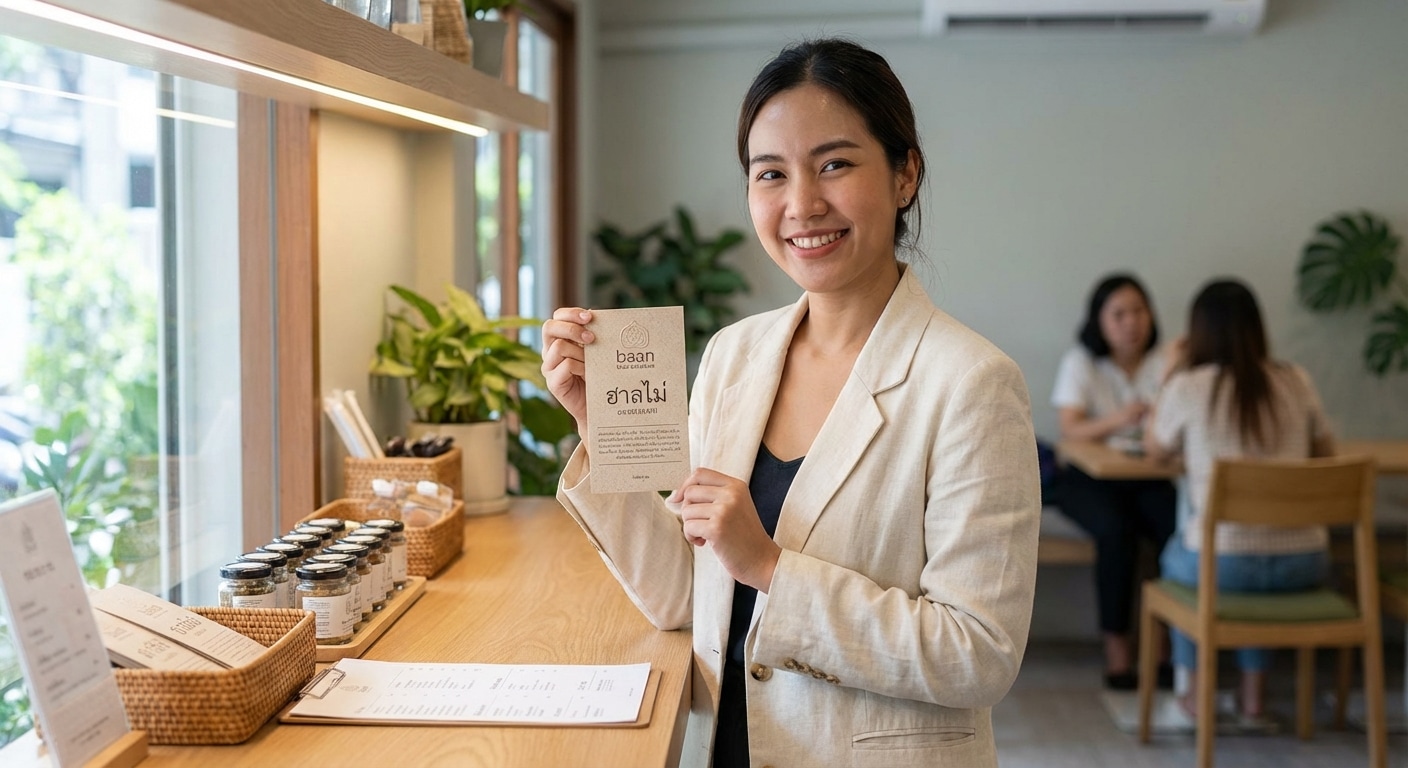
- ความหรูหราแบบทันสมัย (Modern Luxury): เทรนด์ฟอนต์ปี 2026 มุ่งเน้นการสร้างความรู้สึกพรีเมียมผ่านการใช้ตัวอักษรขนาดใหญ่ (Oversized) ฟอนต์เชิงทดลอง (Experimental) และการผสมผสานวัฒนธรรม (Cross-Cultural) เพื่อสร้างเอกลักษณ์ที่โดดเด่น
- จิตวิทยาผ่านตัวอักษร: ฟอนต์ที่มีความโค้งมนให้ความรู้สึกอบอุ่นและเป็นมิตร ในขณะที่ฟอนต์แบบ Serif สื่อถึงความน่าเชื่อถือและความคลาสสิก การเลือกใช้ที่เหมาะสมช่วยสร้างความไว้วางใจให้กับแบรนด์
- เอกลักษณ์ความเป็นไทยในบริบทสากล: การนำแรงบันดาลใจจากรากเหง้าของตัวอักษรไทยโบราณมาผสมผสานกับการออกแบบสมัยใหม่ เป็นอีกหนึ่งแนวทางที่ช่วยสร้างความแตกต่างและน่าจดจำในตลาดโลก
- ความยืดหยุ่นในยุคดิจิทัล: อัตลักษณ์องค์กร (Corporate Identity) ที่ยืดหยุ่นสามารถปรับเปลี่ยนโลโก้หรือตัวอักษรตามบริบทของสื่อดิจิทัลได้ จะช่วยสร้างความทันสมัยและเพิ่มการมีส่วนร่วมของผู้บริโภค
- ฟอนต์มีผลต่อยอดขาย: การปรับเปลี่ยนฟอนต์บนบรรจุภัณฑ์ เมนูอาหาร หรือสื่อประชาสัมพันธ์ สามารถยกระดับการรับรู้มูลค่าของสินค้าและบริการ นำไปสู่การเพิ่มขึ้นของยอดขายได้อย่างมีนัยสำคัญ
ทำไมการเลือกฟอนต์จึงเป็นมากกว่าแค่ความสวยงามในปี 2026
ในยุคที่ผู้บริโภคถูกรายล้อมด้วยข้อมูลและสื่อต่างๆ มากมาย การสร้างความประทับใจแรก (First Impression) กลายเป็นสิ่งสำคัญอย่างยิ่ง ตัวอักษร หรือ Typography คือหนึ่งในองค์ประกอบแรกๆ ที่ผู้บริโภคสัมผัสและมีปฏิสัมพันธ์ด้วย ไม่ว่าจะเป็นบนโลโก้, บรรจุภัณฑ์สินค้า, เว็บไซต์ หรือโพสต์บนโซเชียลมีเดีย ฟอนต์สามารถกำหนดการรับรู้ของลูกค้าที่มีต่อแบรนด์ได้ทันที ก่อนที่พวกเขาจะได้อ่านเนื้อหาทั้งหมดด้วยซ้ำ
สำหรับผู้ประกอบการขนาดกลางและขนาดย่อม (SME), นักออกแบบ, และนักการตลาดในประเทศไทย การเข้าใจเทรนด์ฟอนต์ปี 2026 จึงเป็นสิ่งจำเป็น ข้อมูลพฤติกรรมผู้บริโภคชี้ให้เห็นว่าคนไทยใช้เวลากับโซเชียลมีเดียโดยเฉลี่ยถึง 20 ชั่วโมง 45 นาทีต่อสัปดาห์ ซึ่งหมายความว่าแบรนด์มีโอกาสสร้างการรับรู้ผ่านภาพลักษณ์บนแพลตฟอร์มดิจิทัลได้อย่างมหาศาล การเลือกฟอนต์ที่ทันสมัย สื่อสารตัวตนของแบรนด์ได้ชัดเจน และสอดคล้องกับเทรนด์ระดับโลกที่ปรับใช้กับบริบทไทย จะช่วยให้แบรนด์ของคุณโดดเด่นจากคู่แข่ง สร้างความน่าเชื่อถือ และกระตุ้นให้เกิดการจดจำ ซึ่งท้ายที่สุดแล้วจะนำไปสู่ความภักดีต่อแบรนด์และยอดขายที่เพิ่มขึ้น
เจาะลึก 5 เทรนด์ฟอนต์ไทยที่จะกำหนดทิศทางของแบรนด์ในปี 2026
แนวโน้มการออกแบบตัวอักษรในปี 2026 สะท้อนถึงความต้องการของผู้บริโภคที่มองหาทั้งความหรูหรา ความจริงใจ และประสบการณ์ที่ไม่เหมือนใคร เทรนด์เหล่านี้สามารถนำมาปรับใช้กับตัวอักษรไทยเพื่อสร้างสรรค์งานออกแบบที่ทรงพลังและตอบโจทย์ตลาดได้อย่างลงตัว
เทรนด์ที่ 1: Bold & Experimental Typography – พลังของตัวอักษรเชิงทดลองขนาดใหญ่
เทรนด์นี้คือการฉีกกรอบการออกแบบตัวอักษรแบบเดิมๆ โดยเน้นการใช้ฟอนต์ขนาดใหญ่พิเศษ (Oversized) และการจัดวางองค์ประกอบที่ท้าทายสายตา เพื่อสร้างจุดสนใจและสื่อสารข้อความหลัก (Key Message) อย่างทรงพลัง
ลักษณะเด่น: การใช้ฟอนต์ที่มีน้ำหนักมาก (Bold, Extra Bold, Black) หรือฟอนต์ประเภท Serif ที่มีรายละเอียดของเส้นสายที่ซับซ้อนและสวยงาม มาขยายให้มีขนาดใหญ่จนกลายเป็นองค์ประกอบหลักของงานออกแบบ การจัดวางอาจจะไม่เป็นระเบียบตามปกติ เพื่อสร้างความรู้สึกที่แปลกใหม่และน่าตื่นเต้น แนวคิดนี้มุ่งสร้างความรู้สึกแบบ Modern Luxury ที่ทำให้แบรนด์ดูมีระดับและน่าจดจำ
การประยุกต์ใช้กับแบรนด์ไทย: เหมาะอย่างยิ่งสำหรับแบรนด์แฟชั่น, นิตยสาร, สินค้าไลฟ์สไตล์, หรือธุรกิจที่ต้องการสร้างภาพลักษณ์ที่กล้าหาญและเป็นผู้นำ สามารถนำไปใช้บนหน้าปกสินค้า, โปสเตอร์โฆษณา, ป้ายหน้าร้าน หรือเป็นภาพ Hero Image บนหน้าเว็บไซต์ เพื่อดึงดูดความสนใจได้ในทันที
เทรนด์ที่ 2: Smooth It Over – ความละมุนนุ่มนวลที่สร้างความไว้วางใจ
สวนทางกับความแข็งกร้าวของเทรนด์แรก เทรนด์นี้มุ่งเน้นไปที่การใช้ฟอนต์ที่มีความโค้งมน ลดเหลี่ยมมุมที่แหลมคม เพื่อสร้างความรู้สึกที่อบอุ่น, เป็นมิตร, เข้าถึงง่าย และน่าไว้วางใจ แต่ยังคงไว้ซึ่งความหรูหราและพรีเมียม
ลักษณะเด่น: ตัวอักษรจะมีลักษณะกลมมน ปลายเส้นมักจะโค้งมนแทนที่จะเป็นเส้นตัดตรง ให้ความรู้สึกนุ่มนวลสบายตา จิตวิทยาของรูปทรงโค้งมนสื่อถึงความปลอดภัย ความสบายใจ และความเป็นกันเอง
การประยุกต์ใช้กับแบรนด์ไทย: เหมาะสมอย่างยิ่งกับแบรนด์ที่เกี่ยวข้องกับสุขภาพและความงาม, ผลิตภัณฑ์สำหรับแม่และเด็ก, ธุรกิจอาหารและเครื่องดื่ม, ธุรกิจบริการ เช่น สปา, คลินิก หรือคาเฟ่ที่ต้องการสร้างบรรยากาศที่เป็นมิตรและเชื้อเชิญ การใช้ฟอนต์ลักษณะนี้บนโลโก้หรือบรรจุภัณฑ์จะช่วยสร้างความสัมพันธ์ที่ดีกับลูกค้าและทำให้แบรนด์ดูน่าเชื่อถือ
เทรนด์ที่ 3: Cross-Cultural Type – เสน่ห์ข้ามวัฒนธรรมในตัวอักษรไทย
เทรนด์นี้คือการเฉลิมฉลองความเป็นเอกลักษณ์ทางวัฒนธรรม โดยการนำองค์ประกอบจากรากเหง้าของตัวอักษรในแต่ละท้องถิ่นมาผสมผสานกับการออกแบบที่ทันสมัย เพื่อสร้างอัตลักษณ์ที่ไม่เหมือนใคร
ลักษณะเด่น: การดึงแรงบันดาลใจจากรูปแบบตัวอักษรไทยย้อนยุค, ตัวอักษรที่มีเชิงฐานแบบไทย, หรือแม้กระทั่งการนำลวดลายจากงานหัตถกรรมพื้นบ้านมาประยุกต์เป็นส่วนหนึ่งของตัวอักษร ผลลัพธ์ที่ได้คือฟอนต์ที่มีเรื่องราว มีความสดใหม่ และสื่อถึงความเป็นต้นตำรับอย่างชัดเจน
การประยุกต์ใช้กับแบรนด์ไทย: เป็นโอกาสที่ดีสำหรับแบรนด์ที่ต้องการชูจุดเด่นความเป็นไทย เช่น สินค้า OTOP ที่ต้องการยกระดับสู่ตลาดพรีเมียม, โรงแรมและรีสอร์ท, ร้านอาหารไทย, หรือแบรนด์ผลิตภัณฑ์สมุนไพร การใช้ฟอนต์ลักษณะนี้ช่วยสร้างความแตกต่างที่น่าสนใจและดึงดูดทั้งลูกค้าชาวไทยและชาวต่างชาติ
เทรนด์ที่ 4: Pharma Serif – ความหรูหราจากแรงบันดาลใจยุคเก่า
ได้รับแรงบันดาลใจจากฟอนต์ประเภท Serif ที่มีโครงสร้างชัดเจนและอ่านง่าย ซึ่งเคยนิยมใช้บนบรรจุภัณฑ์ยาในอดีต แต่ถูกนำมาตีความใหม่ให้มีความทันสมัยและหรูหรามากขึ้น
ลักษณะเด่น: เป็นฟอนต์ Serif ที่มีความสมดุลระหว่างประโยชน์ใช้สอย (Utilitarian) และความสวยงามทางศิลปะ มีรายละเอียดของเส้นที่คมชัดและสง่างาม ให้ความรู้สึกน่าเชื่อถือ, เป็นทางการ, และมีคุณภาพสูง
การประยุกต์ใช้กับแบรนด์ไทย: เหมาะสำหรับแบรนด์ที่ต้องการสร้างภาพลักษณ์ของความเชี่ยวชาญและความน่าเชื่อถือ เช่น แบรนด์เวชสำอาง (Dermo-cosmetics), ผลิตภัณฑ์ดูแลสุขภาพระดับพรีเมียม, ธุรกิจที่ปรึกษา, หรือสถาบันการเงิน การใช้ฟอนต์ Pharma Serif ในโลโก้หรือหัวข้อสำคัญจะช่วยสร้างสมดุลระหว่างความคลาสสิกและความทันสมัยได้อย่างลงตัว
เทรนด์ที่ 5: Lingua-Lettering & Halftone Blur – ลูกเล่นทางภาษาและภาพที่น่าจดจำ
เทรนด์สุดท้ายนี้เน้นไปที่การสร้างสรรค์ลูกเล่นทางภาพเพื่อดึงดูดความสนใจในโลกดิจิทัลที่เต็มไปด้วยการแข่งขัน โดยใช้เทคนิคที่สนุกสนานและน่าจดจำ
ลักษณะเด่น: มีสองแนวทางหลัก คือ Lingua-Lettering ซึ่งเป็นการผสมผสานตัวอักษรจากหลายภาษา (เช่น ไทยและอังกฤษ) เข้าไว้ด้วยกันอย่างมีศิลปะ และ Halftone Blur คือการใช้เทคนิคจุดไข่ปลา (Dots) ขนาดใหญ่มาสร้างเป็นตัวอักษรหรือพื้นหลัง ทำให้เกิดเอฟเฟกต์ที่ดูเบลอแต่ยังมีโครงสร้างที่ชัดเจน
การประยุกต์ใช้กับแบรนด์ไทย: เหมาะสมอย่างยิ่งสำหรับการสร้างแบรนด์บนแพลตฟอร์มดิจิทัล เช่น คอนเทนต์สำหรับโซเชียลมีเดีย, แบนเนอร์โฆษณาออนไลน์, หรือแคมเปญการตลาดที่ต้องการสร้างกระแส (Viral) เทคนิคนี้ช่วยให้แบรนด์ดูทันสมัย, เข้าถึงง่าย, และสร้างการมีส่วนร่วมกับกลุ่มเป้าหมายที่เป็นคนรุ่นใหม่ได้เป็นอย่างดี
สรุปภาพรวมเทรนด์ฟอนต์ไทย 2026
| เทรนด์ (Trend) | ลักษณะเด่น (Key Feature) | เหมาะกับธุรกิจประเภท | สร้างความรู้สึก (Evokes Feeling) |
|---|---|---|---|
| Bold & Experimental | ตัวอักษรขนาดใหญ่, จัดวางแปลกใหม่, Serif รายละเอียดสูง | แฟชั่น, ไลฟ์สไตล์, นิตยสาร, แบรนด์ที่ต้องการเป็นผู้นำ | หรูหรา, ทันสมัย, กล้าหาญ, โดดเด่น |
| Smooth It Over | ฟอนต์โค้งมน, ลดมุมแหลม, นุ่มนวล | สุขภาพ, ความงาม, สินค้าเด็ก, คาเฟ่, สปา | อบอุ่น, เป็นมิตร, น่าไว้วางใจ, เข้าถึงง่าย |
| Cross-Cultural Type | ผสมผสานรากเหง้าวัฒนธรรมไทยกับการออกแบบสมัยใหม่ | สินค้า OTOP, ร้านอาหารไทย, โรงแรม, แบรนด์ที่มีเรื่องราว | มีเอกลักษณ์, น่าค้นหา, จริงใจ, มีเรื่องราว |
| Pharma Serif | Serif ที่มีโครงสร้างชัดเจน, สมดุล, สง่างาม | เวชสำอาง, การเงิน, ที่ปรึกษา, แบรนด์ที่เน้นความเชี่ยวชาญ | น่าเชื่อถือ, เป็นมืออาชีพ, มีคุณภาพ, คลาสสิก |
| Lingua-Lettering | ผสมหลายภาษา, ใช้เทคนิคภาพ (Halftone) | แบรนด์ดิจิทัล, สินค้าสำหรับคนรุ่นใหม่, แคมเปญการตลาด | สนุกสนาน, ทันสมัย, สร้างสรรค์, น่าจดจำ |
กลยุทธ์การเลือกและจับคู่ฟอนต์ไทยสำหรับ SME
การรู้จักเทรนด์เป็นเพียงจุดเริ่มต้น สิ่งที่สำคัญกว่าคือการนำไปปรับใช้ให้เข้ากับแบรนด์ของตนเองได้อย่างมีประสิทธิภาพ การเลือกและจับคู่ฟอนต์ไม่ใช่เรื่องที่ซับซ้อนหากเข้าใจหลักการพื้นฐาน
หลักการพื้นฐานในการจับคู่ฟอนต์
- สร้างความแตกต่าง (Contrast): หลักการที่สำคัญที่สุดคือการจับคู่ฟอนต์ที่มีความแตกต่างกันอย่างชัดเจน เช่น การใช้ฟอนต์แบบ Serif (มีเชิง) สำหรับหัวข้อ และใช้ฟอนต์ Sans-serif (ไม่มีหัว) สำหรับเนื้อหา เพื่อสร้างลำดับชั้นในการอ่านและทำให้ข้อความอ่านง่ายขึ้น
- กำหนดลำดับชั้นของข้อมูล (Hierarchy): ใช้ขนาด, น้ำหนัก (ความหนา), และสไตล์ของฟอนต์เพื่อนำทางสายตาของผู้อ่าน หัวข้อหลักควรโดดเด่นที่สุด ตามมาด้วยหัวข้อย่อย และเนื้อหาตามลำดับ
- รักษาบุคลิกของแบรนด์ (Brand Personality): ฟอนต์ที่เลือกใช้ต้องสอดคล้องกับบุคลิกของแบรนด์ หากแบรนด์ของคุณดูสนุกสนานและเป็นกันเอง การเลือกใช้ฟอนต์ที่เป็นทางการและเคร่งขรึมอาจสร้างความสับสนให้กับลูกค้าได้
- จำกัดจำนวนฟอนต์: เพื่อความเป็นระเบียบและไม่ทำให้งานออกแบบดูรกจนเกินไป ควรจำกัดการใช้ฟอนต์ในงานออกแบบหนึ่งชิ้นไว้ที่ไม่เกิน 2-3 ฟอนต์
การจับคู่ฟอนต์ที่ดีเปรียบเสมือนการเลือกเสื้อผ้าที่เข้าชุดกันอย่างลงตัว มันสามารถยกระดับภาพลักษณ์โดยรวมให้ดูดีขึ้นได้อย่างไม่น่าเชื่อ
ตัวอย่างฟอนต์ที่น่าสนใจและรองรับภาษาไทย
ในปัจจุบันมีฟอนต์คุณภาพสูงมากมายที่ออกแบบมาเพื่อรองรับภาษาไทยโดยเฉพาะ ซึ่งสามารถตอบโจทย์เทรนด์ปี 2026 ได้เป็นอย่างดี:
- ฟอนต์ตระกูล Modernist: เช่น Sharp Grotesk Global ที่รองรับภาษาไทย มีหลายน้ำหนักและความกว้างให้เลือกใช้ ทำให้มีความยืดหยุ่นสูง เหมาะกับการสร้างแบรนด์ที่ต้องการความทันสมัยและดูเป็นสากล
- ฟอนต์ตระกูล Humanist Sans-serif: เช่น National 2 ที่ได้รับการปรับปรุงให้มีสัดส่วนที่สมดุลและอ่านง่ายบนหน้าจอ เหมาะสำหรับงาน Web Typography และการสร้างอัตลักษณ์องค์กรที่ต้องการความเป็นมิตรและอ่านง่าย
- ฟอนต์ไทยจากแหล่งข้อมูลเฉพาะทาง: แหล่งรวมฟอนต์อย่าง Thaifaces มีฟอนต์ไทยหลากหลายรูปแบบให้เลือก ทั้งแบบมีเชิงฐาน, ย้อนยุค, ดิสเพลย์, และแบบประดิษฐ์ ซึ่งเหมาะอย่างยิ่งสำหรับการสร้างโลโก้และงานออกแบบที่ต้องการอัตลักษณ์ความเป็นไทยที่ชัดเจน
ผลกระทบของฟอนต์ต่อยอดขายและอัตลักษณ์องค์กร (CI)
การตัดสินใจเปลี่ยนฟอนต์ไม่ใช่แค่เรื่องของการปรับโฉม แต่เป็นการลงทุนเชิงกลยุทธ์ที่ส่งผลกระทบโดยตรงต่อธุรกิจ การเลือกฟอนต์ที่สอดคล้องกับเทรนด์และบุคลิกของแบรนด์จะช่วยสร้าง อัตลักษณ์องค์กร (Corporate Identity – CI) ที่แข็งแกร่งและน่าจดจำ ในยุคดิจิทัล แนวคิดของ Flexible CI Manual หรือคู่มืออัตลักษณ์ที่ยืดหยุ่น กำลังได้รับความนิยม โดยแบรนด์สามารถปรับเปลี่ยนการแสดงผลของโลโก้หรือฟอนต์ให้เข้ากับบริบทของแต่ละแพลตฟอร์มได้ ซึ่งช่วยสร้างความทันสมัยและเข้าถึงผู้บริโภคได้ดียิ่งขึ้น
เมื่อ CI มีความชัดเจนและน่าเชื่อถือ ย่อมนำไปสู่การสร้าง ความไว้วางใจ (Trust) ในหมู่ผู้บริโภค ความไว้วางใจนี้เป็นปัจจัยสำคัญที่ส่งผลต่อการตัดสินใจซื้อ เมื่อลูกค้ารู้สึกว่าแบรนด์ดูเป็นมืออาชีพ มีคุณภาพ และใส่ใจในรายละเอียดเล็กๆ น้อยๆ อย่างการเลือกใช้ฟอนต์ พวกเขาย่อมมีแนวโน้มที่จะเลือกซื้อสินค้าและบริการจากแบรนด์นั้นมากกว่าคู่แข่ง สิ่งนี้จะสะท้อนกลับมาเป็นยอดขายที่เพิ่มขึ้นและการเติบโตของธุรกิจในระยะยาว
บทสรุป: อนาคตของแบรนด์เริ่มต้นที่ตัวอักษร
สรุปได้ว่า 5 เทรนด์ตัวอักษรไทยในปี 2026 ไม่ว่าจะเป็นการใช้ตัวอักษรขนาดใหญ่เชิงทดลอง, ความโค้งมนที่สร้างความไว้วางใจ, การผสมผสานวัฒนธรรม, ความหรูหราแบบ Pharma Serif, หรือลูกเล่นทางดิจิทัล ล้วนเป็นเครื่องมืออันทรงพลังสำหรับธุรกิจ SME ในการสร้างแบรนด์ให้ดูแพงและโดดเด่น การเลือกใช้ฟอนต์ไม่ใช่เรื่องของรสนิยมส่วนตัวอีกต่อไป แต่เป็นศาสตร์และศิลป์ที่ต้องอาศัยความเข้าใจในจิตวิทยาผู้บริโภคและทิศทางของตลาด
การลงทุนเวลาและทรัพยากรเพื่อเลือกสรรและปรับใช้ฟอนต์ที่เหมาะสมกับแบรนด์ คือการวางรากฐานที่มั่นคงสำหรับอนาคต มันคือการสื่อสารที่เงียบงันแต่ทรงพลังที่สุด ที่จะช่วยให้แบรนด์ของคุณเป็นที่จดจำ น่าเชื่อถือ และประสบความสำเร็จในตลาดที่มีการแข่งขันสูงขึ้นทุกวัน